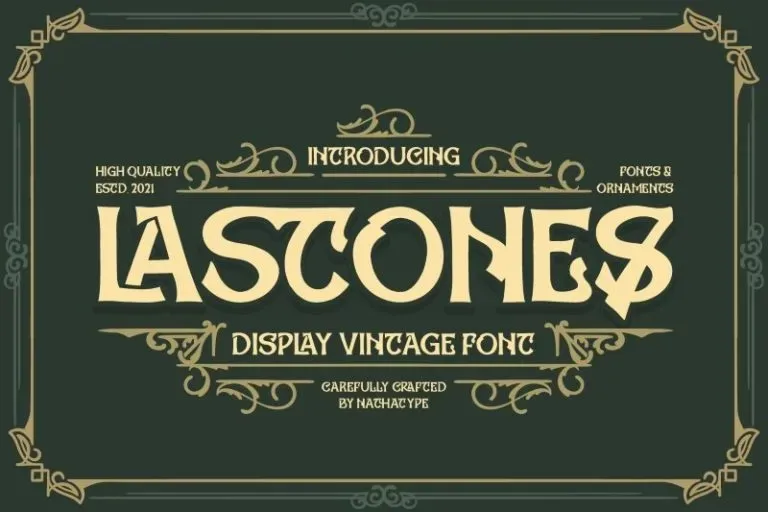
Lastones Font – Download Grátis
Esta font é uma elegante mistura entre a tipografia moderna e clássica, inspirada na arte vintage dos anos 1900. Perfeita para quem quer adicionar um toque nostálgico ao seu projeto sem se tornar excessivamente antigo. A Lastones Font oferece um estilo artístico que é ideal para uma variedade de projetos, desde a criação do logo da sua empresa até o design de capa de livro ou mesmo das camisetas com o seu logotipo. É também perfeita para criar propaganda e publicidade em materiais de promoção, como banners ou outdoors. Ela é uma fonte de tipo multitalentosa que encaixa-se perfeitamente no perfil da 99designs, fornecendo alternativas criativas para qualquer necessidade gráfica.